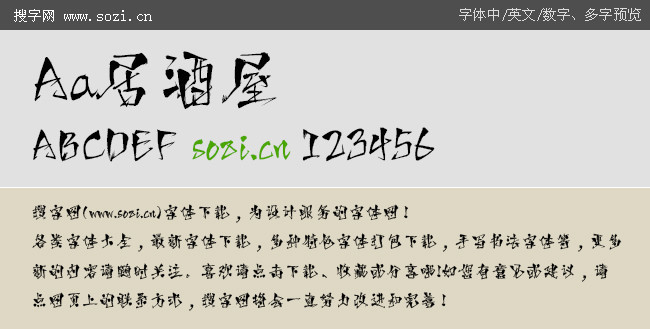
Aa居酒屋
搜字網(wǎng)給大家提供一款A(yù)a居酒屋(非商業(yè)使用)中文字體下載,該字體是一款手寫風(fēng)格中文字體,字形瀟灑大方,霸道十足,非常漂亮,適合包裝設(shè)計(jì)、書裝設(shè)計(jì)、海報(bào)設(shè)計(jì)等應(yīng)用(此字體為個人非商用版,商用可以聯(lián)系QQ:1006760504)。